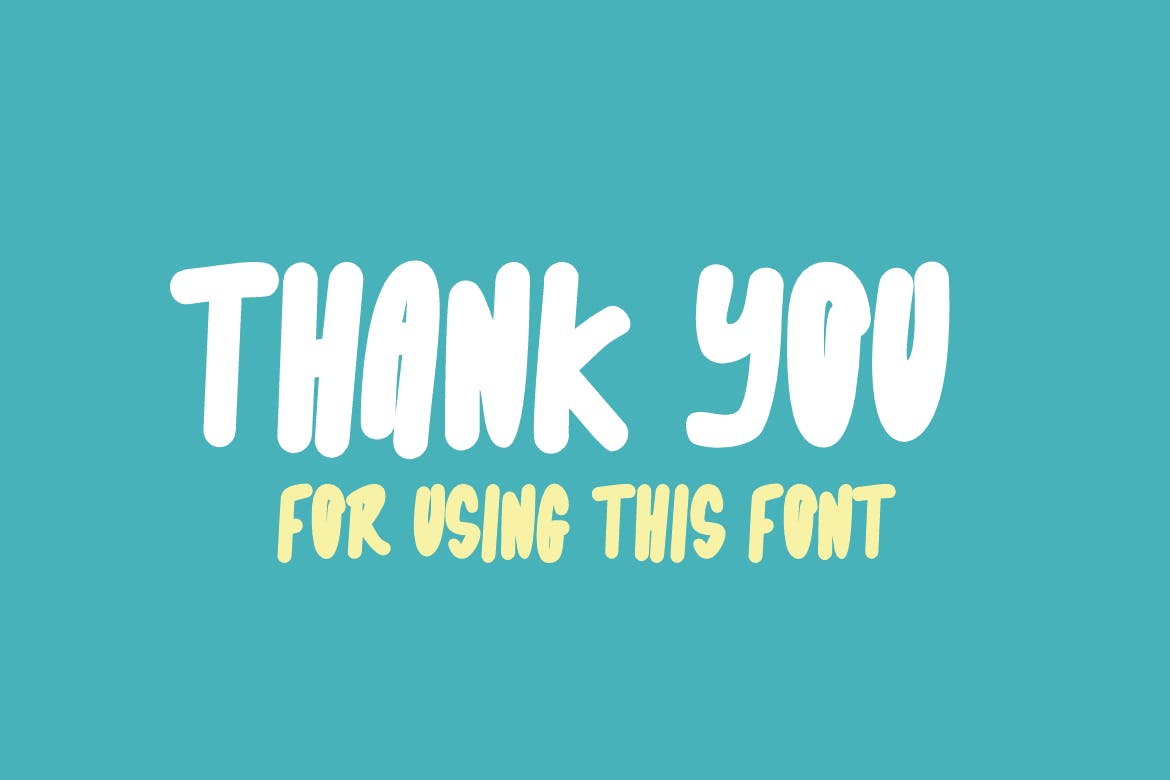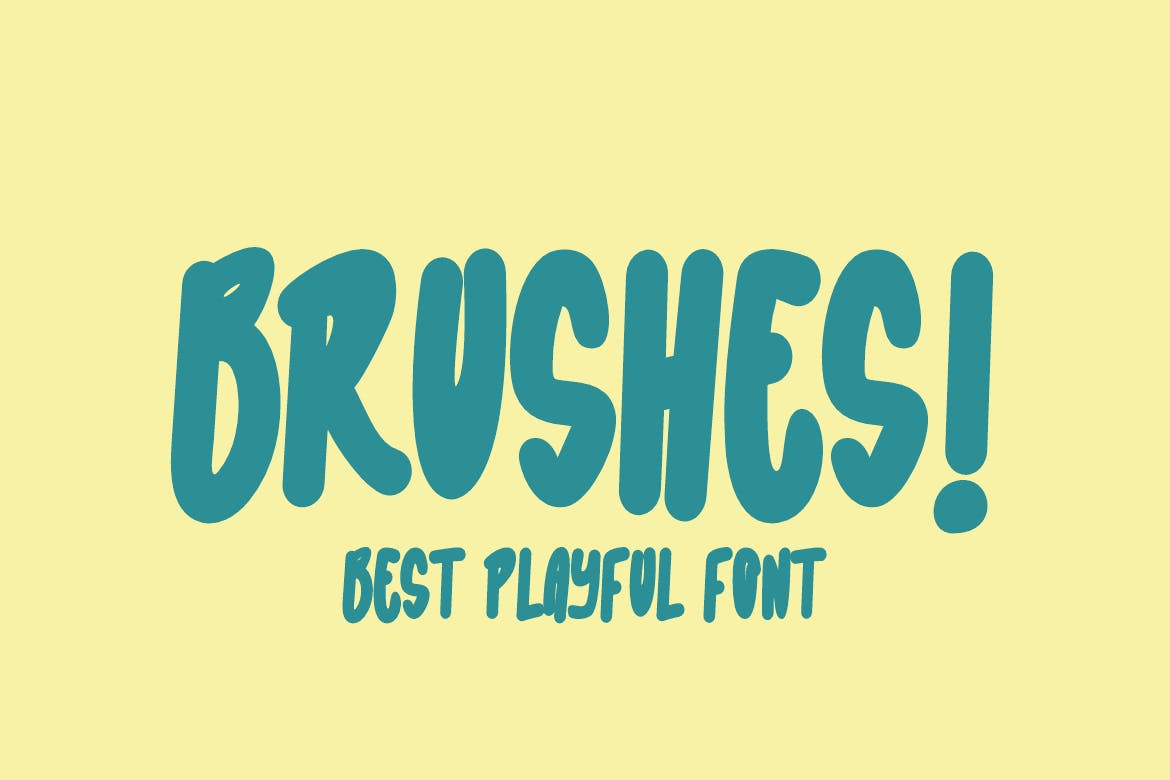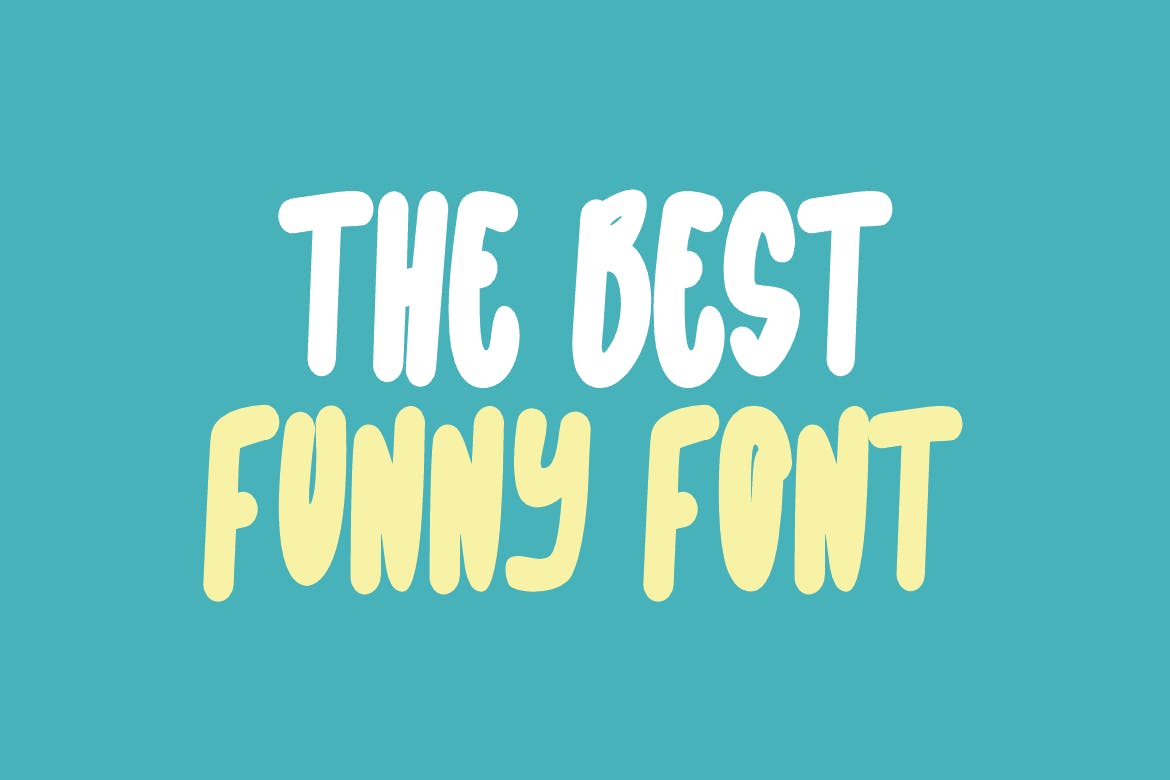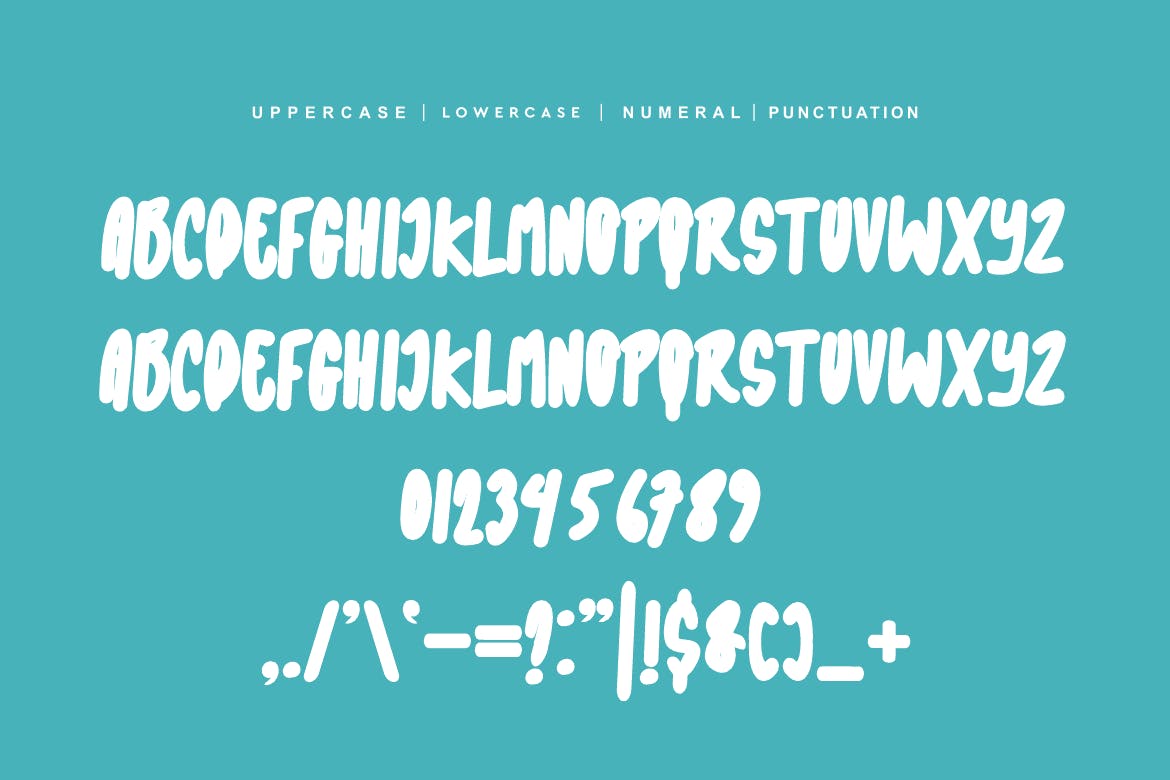
Melisher Playful Font
فونت ملشیر پلیفل، گزینه‌ای ایده‌آل برای پروژه‌های طراحی شماست.
ملشیر - فونت پلیفل یک فونت نمایشگری با طراحی جذاب و هنری است. این فونت برای هر پروژه برندینگ مانند پوستر، لوگو، ورزشی و بسیاری دیگر مناسب می‌باشد. عملکرد عالی آن در زمینه‌های مختلف، آن را به انتخابی ایده‌آل تبدیل کرده است.